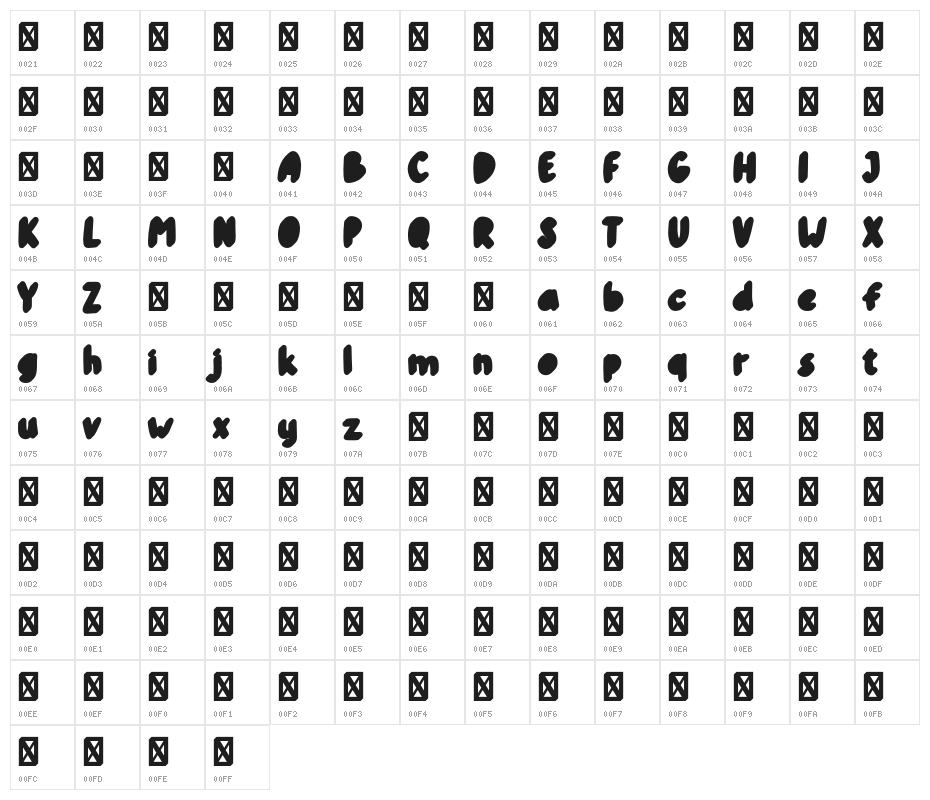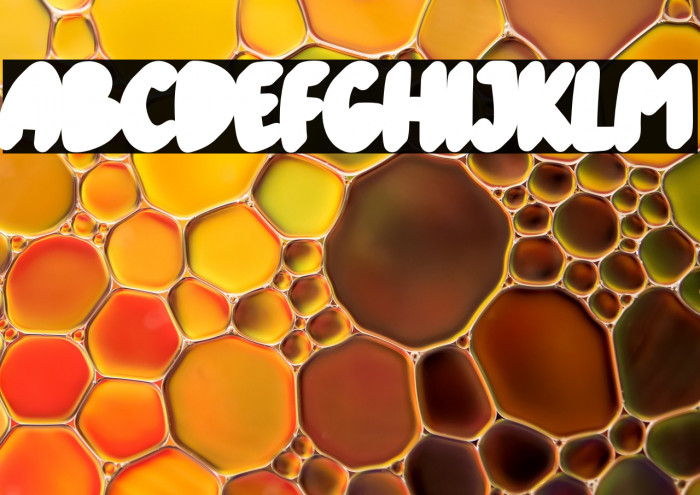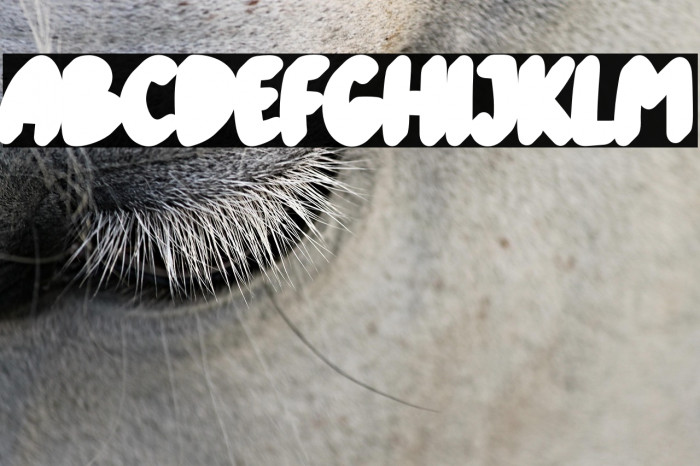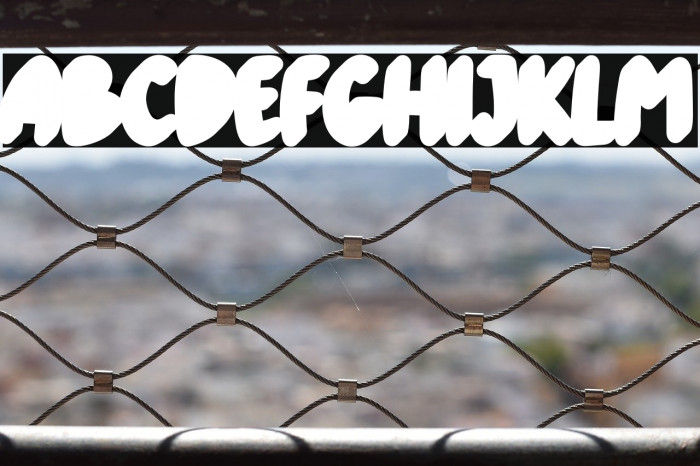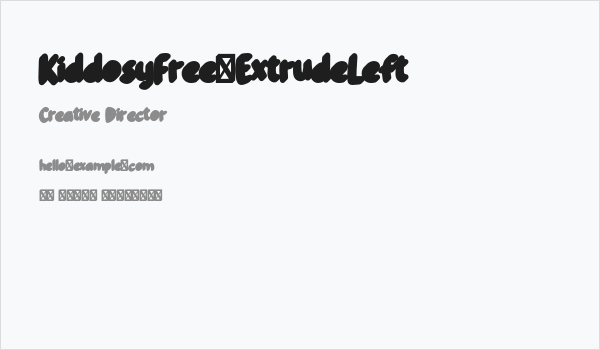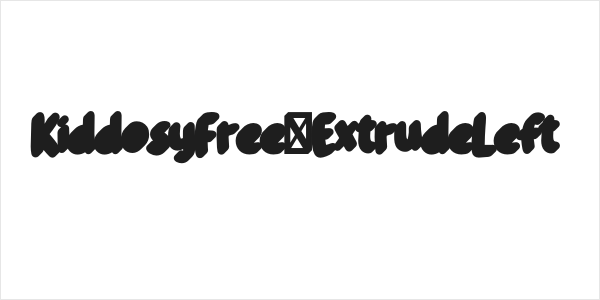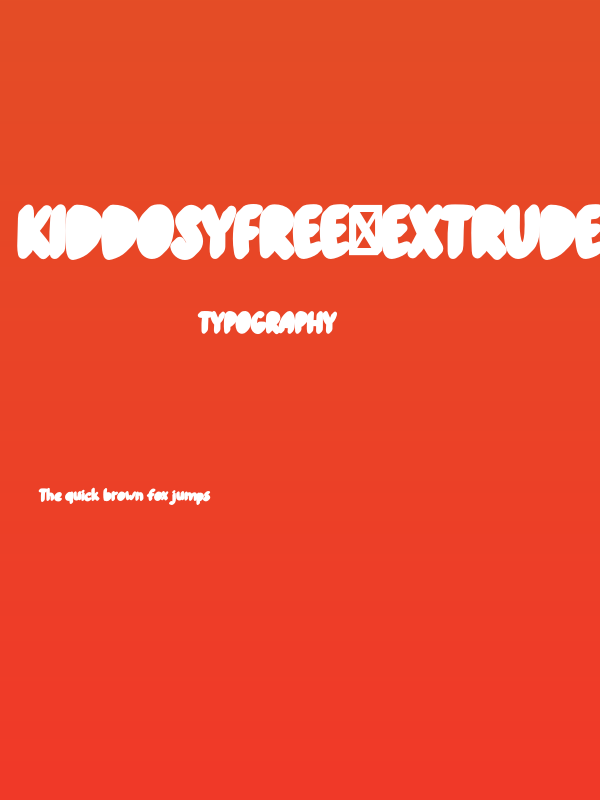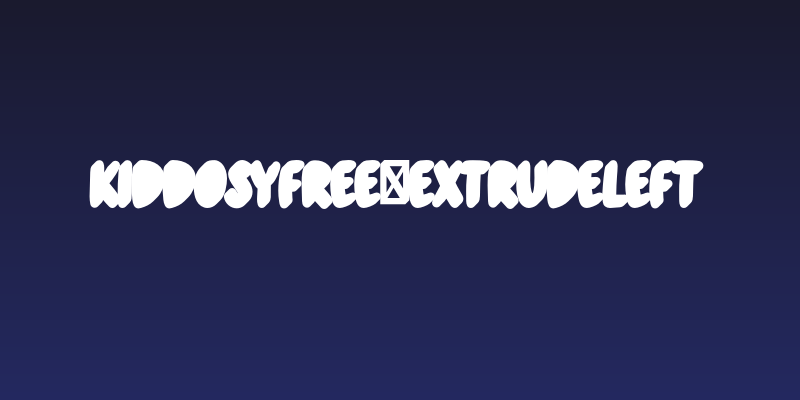
KiddosyFree-ExtrudeLeft Font
| Caso d'uso | Logos, Posters, Children's materials |
| Progetti proposti | Ideal for children's books, playful branding, party invitations, and creative posters. |